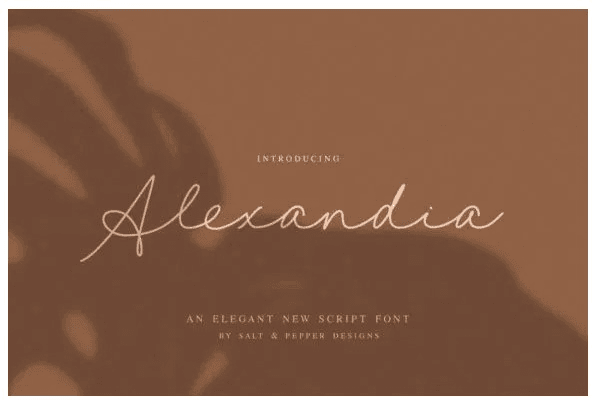
Alexandia Font
Alexandia - это милый и прекрасный рукописный шрифт.
Он имеет красивый поток и гладкое прикосновение. Не слишком тонкая и не слишком толстая, сбалансированная и разнообразная, Alexandia была создана для того, чтобы подчеркнуть красоту ваших проектов.
Alexandia - это милый и прекрасный рукописный шрифт.
Он имеет красивый поток и гладкое прикосновение. Не слишком тонкая и не слишком толстая, сбалансированная и разнообразная, Alexandia была создана для того, чтобы подчеркнуть красоту ваших проектов.